大家是否了解美术字呢?作为现代一种有着极高美观程度的字体,它的使用在年轻人制作的文档文件和聊天交友中被广泛使用,彰显了自己独特的艺术品味。
相信有些读者还是不知道美术字是什么,他是一种我们在基础的简体汉字上,经过设计师的设计加工和美术师的美化装饰,形成的一种美化文字的文字字体。写出的文字,一眼看上去能很明显的进入你的眼睛,非常的醒目,看起来非常的整齐,也没有繁体字和古体汉子那么复杂难以辨认。
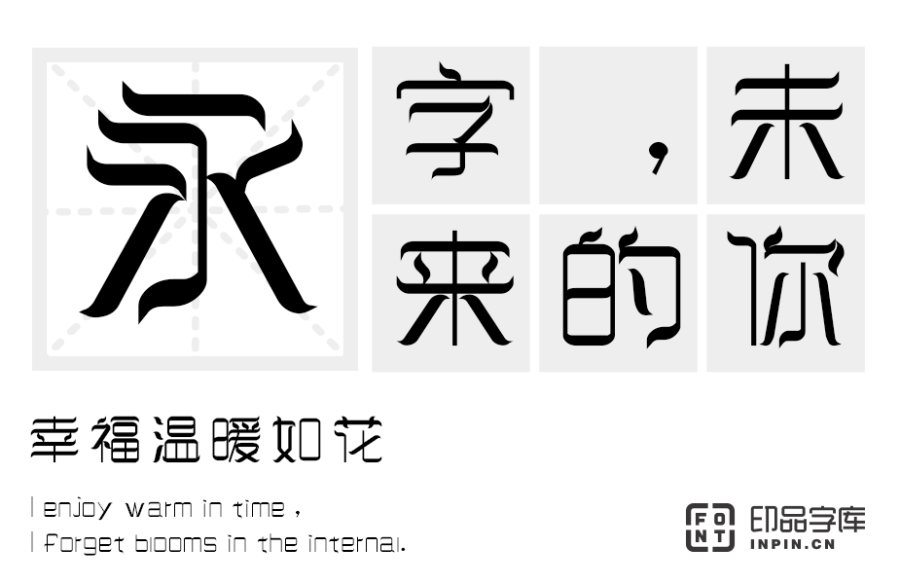
我们平常将美术字转换后就可以用来进行横幅,板报和海报或者一些产品的包装和广告宣传,用美术字的好处就是可以非常显眼让别人很容易就记住,达到事半功倍的效果。那么美术字要从哪里去寻找使用呢?